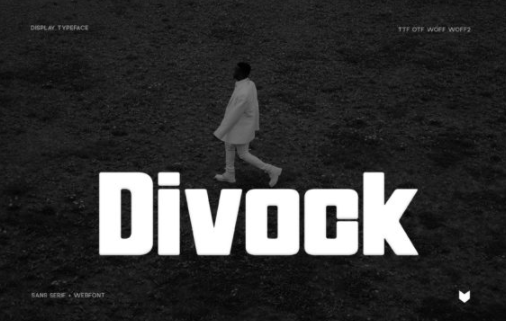
[Creativefabrica] Divock Font (2022)
Divock - это крутой, смелый и толстый шрифт.
Он идеально подходит для написания веб-дизайнов, визитных карточек и практически всего, что требует напористого штриха.
Divock - это крутой, смелый и толстый шрифт.
Он идеально подходит для написания веб-дизайнов, визитных карточек и практически всего, что требует напористого штриха.